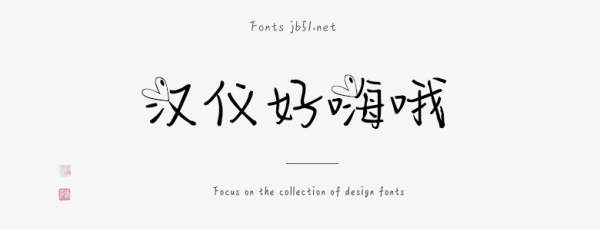
漢儀好嗨哦是由漢儀字庫(kù)出品,字體筆觸纖細(xì),字體以心形圖案作為點(diǎn)綴,具有很好的視覺(jué)感,適合應(yīng)用于藝術(shù)設(shè)計(jì)、平面宣傳設(shè)計(jì)、網(wǎng)頁(yè)設(shè)計(jì),書法字帖等領(lǐng)域,需要的朋友可以前來(lái)本站下載。